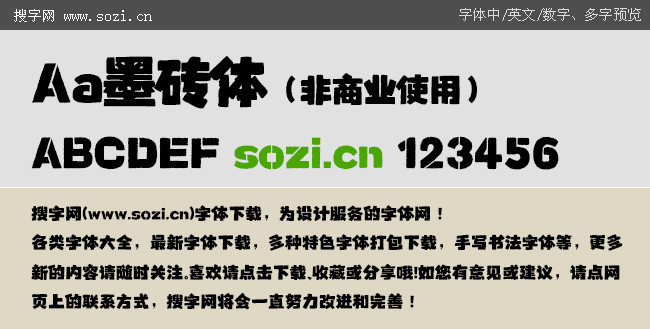
Aa墨磚體
搜字網(wǎng)給大家提供一款A(yù)a墨磚體(非商業(yè)使用)中文字體下載,該字體是一款非常個性的粗體藝術(shù)字體,通過對部分筆型的特殊處理,使字面空間分布更加均勻,風(fēng)格比一般的字體更有特色,連貫字跡顯得干練而不凌亂,清新簡明,適用于平面宣傳設(shè)計、網(wǎng)頁設(shè)計、海報設(shè)計等應(yīng)用(此字體為個人非商用版,商用可以聯(lián)系QQ:1006760504)。